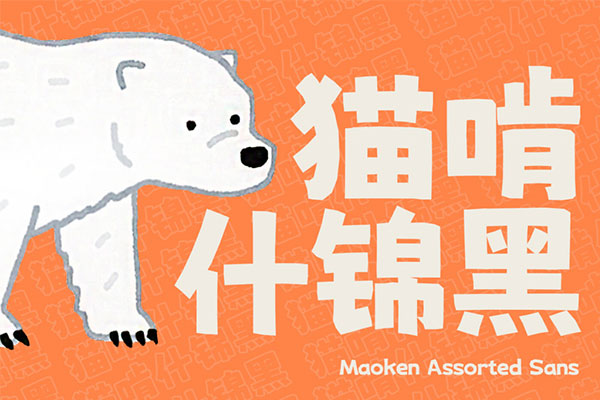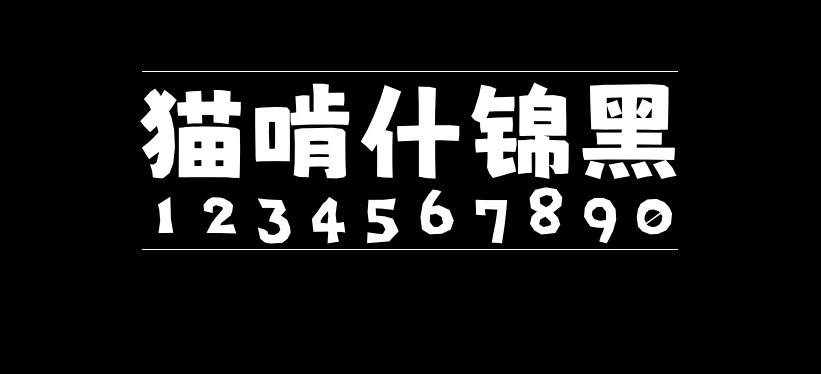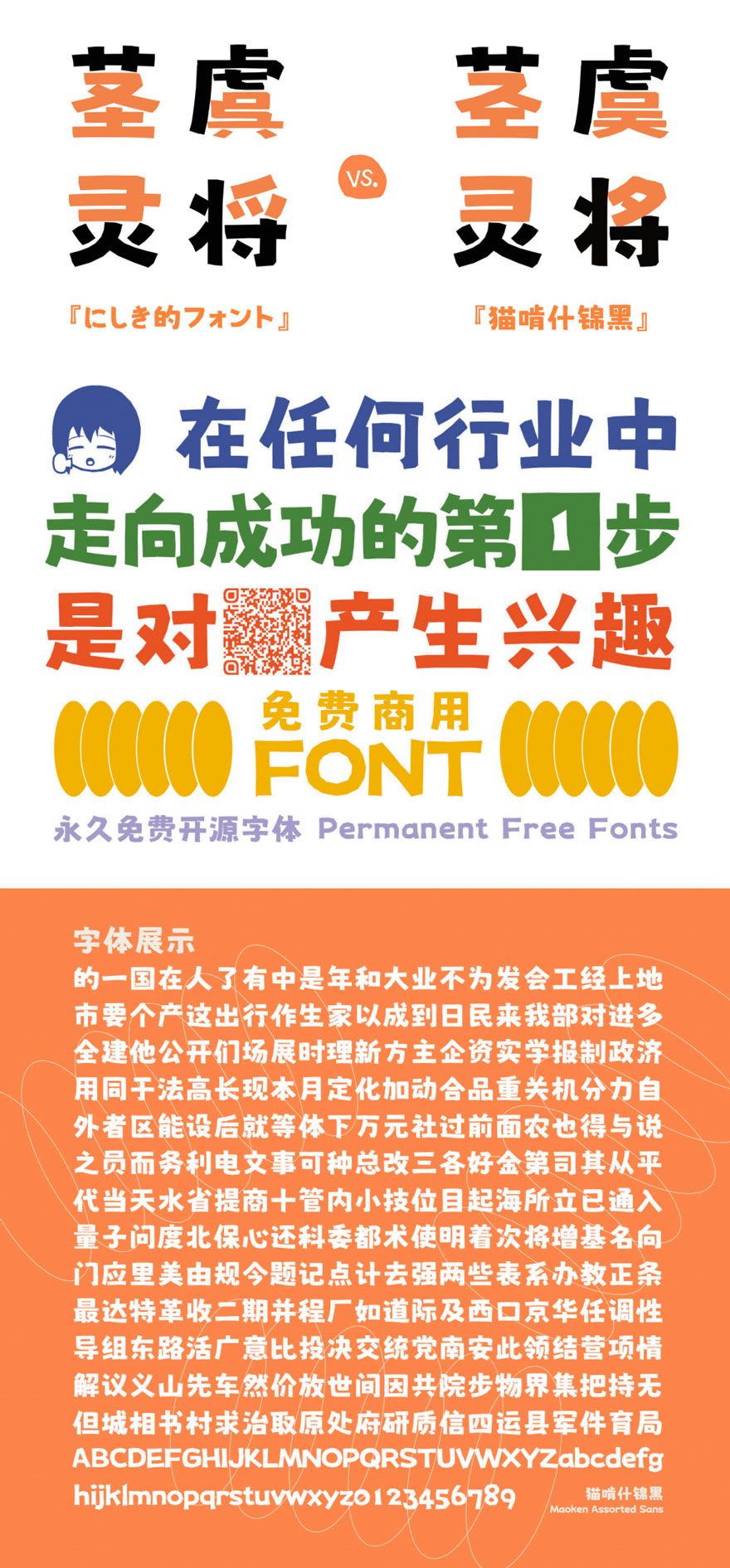
猫啃什锦黑
猫啃什锦黑是基于日本作者Umihotaru创作的字体Nishiki-teki(にしき的フォント)进行简体字补充的一款字体。这个字体的补简工作是由ZERO子主导,联合荆南字坊、时光羊、白日月球、帆影、频凡、Skylinext、阿東東東東、orj等(排名不分先后)一起共同历经千辛万苦完成的。
猫啃什锦黑是一款可爱的马克笔手绘风格免费商用字体,其笔画活泼有趣萌萌哒,特别适合做可爱类、母婴类等海报的标题字体。猫啃什锦黑现已完成简体国标GB2312的6763字增补工作;繁体字型还在继续完善中,繁体支持度也很不错了。